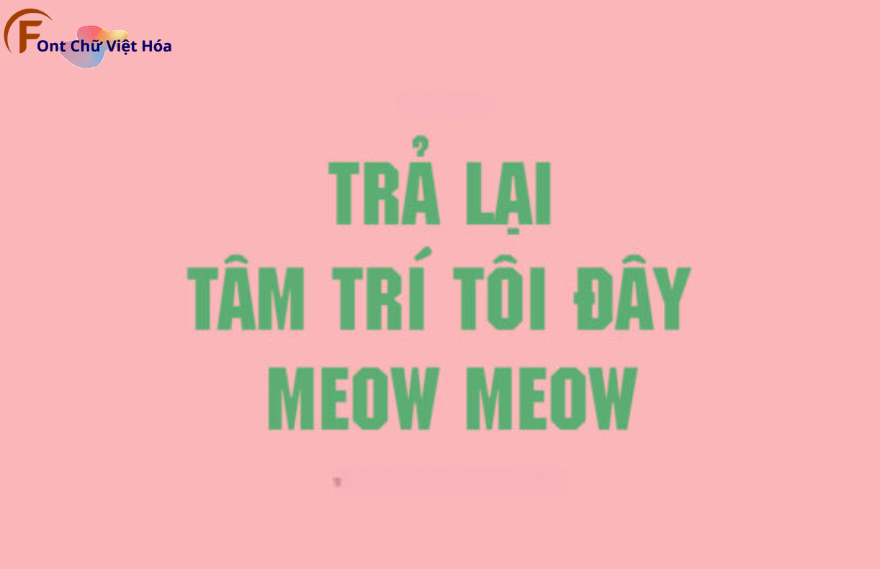
SFU Machine Font Việt Hóa
Phân loại: Cá tính
Kiểu chữ: Không chân
Độ dày: Regular, Bold
SFU Machine Font
SFU Machine Việt Hóa, thuộc bộ font SFU, mang phong cách sans-serif hiện đại với các đường nét mạnh mẽ và cá tính. Font này được thiết kế nhằm mục tiêu tạo ra sự rõ ràng và dễ đọc, đặc biệt phù hợp cho các thiết kế như poster, logo, và tiêu đề. Đặc điểm hình dạng của SFU Machine là các đường nét đậm và tỷ lệ chữ cân đối, giúp tối ưu hóa không gian và tạo ấn tượng thị giác mạnh mẽ. Font này cũng đã được Việt hóa, mang đến sự linh hoạt và tiện dụng cho các dự án thiết kế bằng tiếng Việt, giúp người dùng dễ dàng tiếp cận và sử dụng.
SFU Machine Font việt hóa
SFU Machine font character map